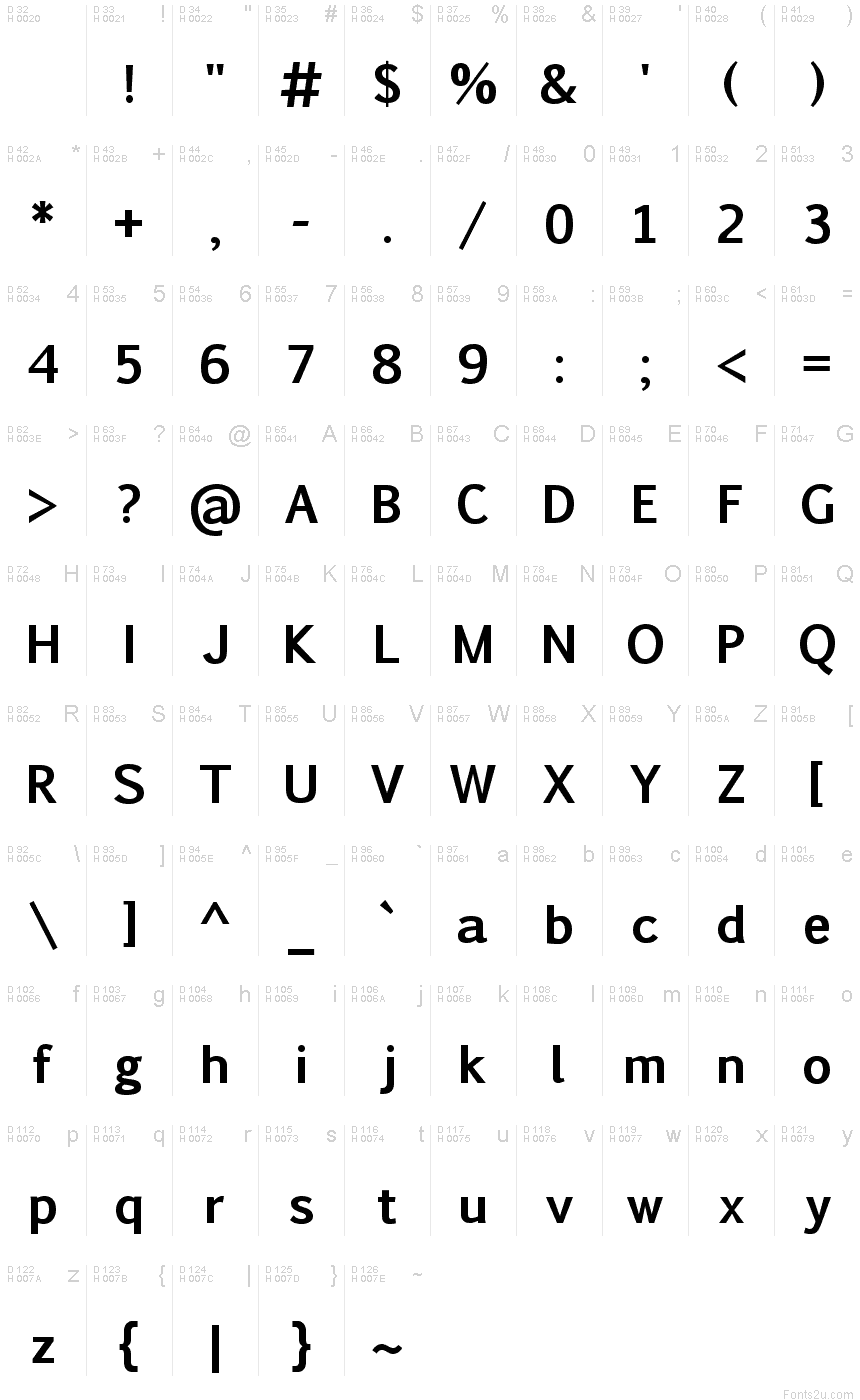
Pigiarniq Bold, eine kostenlose serifenlose Schrift der Regierung von Nunavut, der Legislative Assembly of Nunavut und Tiro Typeworks, besitzt eine warme, bürgernahe Schlichtheit, die eher direkt als neutral wirkt. Schwere Striche, abgerundete Punkte und sympathische einstöckige Formen verleihen den Buchstaben einen stabilen, zugänglichen Rhythmus, während die breiten Kurven verhindern, dass sie mechanisch wirken.
Damit ist sie die ideale kostenlose Schriftart für öffentliche Informationsgrafiken, Museumstafeln, Lehrmaterialien, Gemeindeposter und Leitsysteme, bei denen es auf eine klare, bodenständige Stimme ankommt. Sie eignet sich auch hervorragend für Titel, kurze Cover-Texte und Markenbeschriftungen, da die fetten Kleinbuchstaben selbst bei großen Schriftgraden vertraut und menschlich wirken.
Pigiarniq Inukitut syllabics is a font containing the maximum repertoire of characters included in Canadian Syllabics, as well as roman characters required to support English, French, and all other languages supported by the Codepage 1252. Additional characters are included to support further orthographies including Greenlandic. Inuktitut Syllabic portions of Fonts distributed under the name 'Pigiarniq' are Copyrighted material of the Government of Nunavut. Latin, or non-Inuktitut syllabic portions of the Fonts are Copyrighted material of Tiro Typeworks.